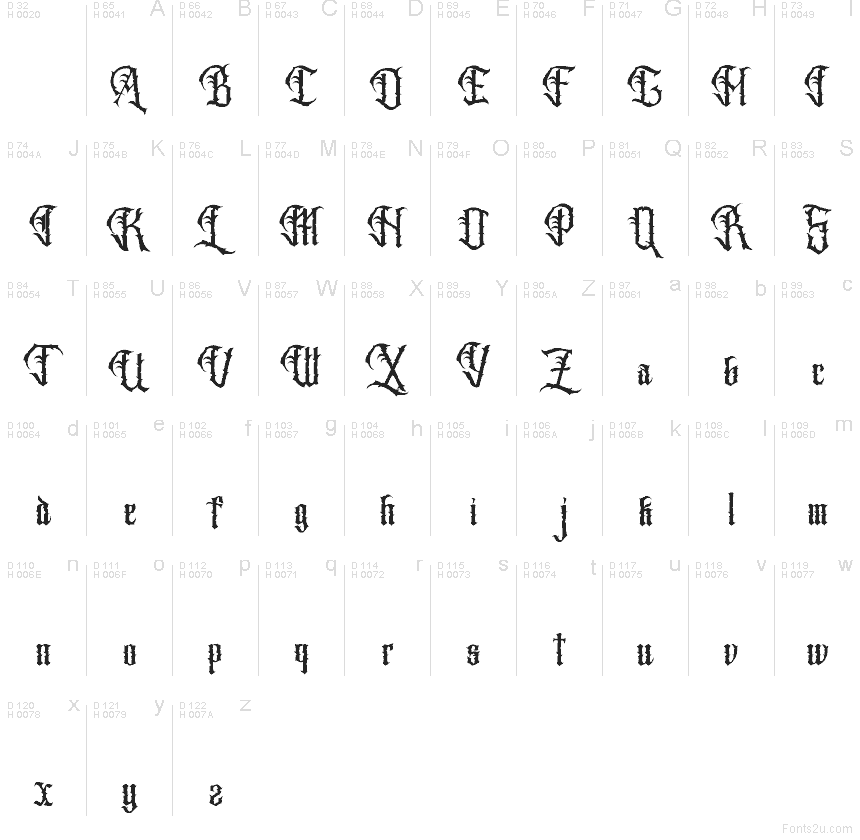
Fluster je bezplatné blackletter display písmo s drsným středověkým nádechem, které proměňuje gotické tvary v řadu ostrých háků, dělených křivek a trnitých ozdob. Písmena působí úzce a ceremoniálně, se špičatými konci a vyrytými zářezy, které dodávají celému písmu přísný, heraldický rytmus, namísto jemného vintage stylu.
Hodí se pro titulky na plakátech, metalové a punkové letáky, obaly desek, branding tetovacích studií a grafiku temných akcí, kde bezplatné písmo s tolika hranatými detaily dokáže samo o sobě vytvořit atmosféru. Použijte ho pro krátké nadpisy, monogramy, titulky na obálkách nebo grafické karty, když chcete, aby písmena vypadala jako vyryté emblémy a ne jako běžný text.
FLUSTER